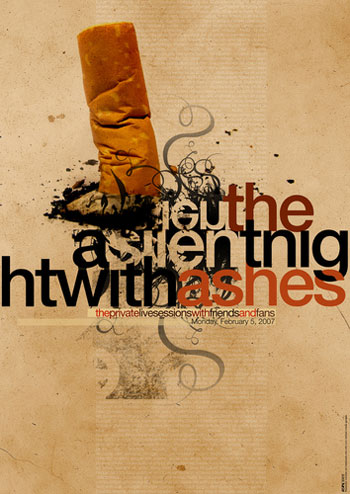
laufweite verringern bei logofonts?
ich weiß es gibt gewisse richtlinien, allerdings frage ich mich schon gerade wie es aussieht bei logofonts mit einer verringerung der laufweite, so dass die einzelnen buchstaben leicht ineinander laufen.
dies wird ja gerade häufig bei der helvetica verwendet.
wie ist da eure meinung zu, es gibt ja doch einige umgesetzte varianten.
zum beispiel folgendes:
Kann man machen, warum nicht ... Speziell im amerikanischen Raum ist das verbreitet.
Genauso kann man weiter setzen, geht für sowas auch. Das eine wirkt dann halt blockartig kompakt, das andere ausladend offen.
Hier irgendwelche "Regeln" aufzustellen, was man machen "darf" und was nicht, ist überflüssig. Es geht ja in so einem Fall nicht darum, massenweise Text lesbar zu machen. Ob und wie gut man die wenigen Worte erfassen kann, hängt dann halt von der Schrift und vom Handwerk ab, und ob man übertreibt oder nicht.
Ein Logo wird gestaltet und nicht gesetzt. Also liegt es beim Gestalter was er mit der Schrift anstellt. :D
wie in den verschiedenen beispielen gezeigt find ich es absolut in ordnung, da es auch gestalterisches merkmal ist und auch harmonisch ist.
also mein geschmack ist es zumoindest.
Gerade beim Logo heißt ja, die Devise, dass es sich auch von inhaltlichen Textmengen absetzen muss. Deshalb empfiehlt sich tatsächlich oftmals die Unterschneidung oder das weite Spationieren. Was ich manchmal als Problem empfinde, ist, wenn Logos klein da stehen. Oft fließen da die zu eng gesetzten Formen ineinander. Dort muss man manchmal zwei Versionen machen: Eine für kleine Größen (mit weiterem Zeichenabstand) und eine für große Größen (mit größerem Zab).